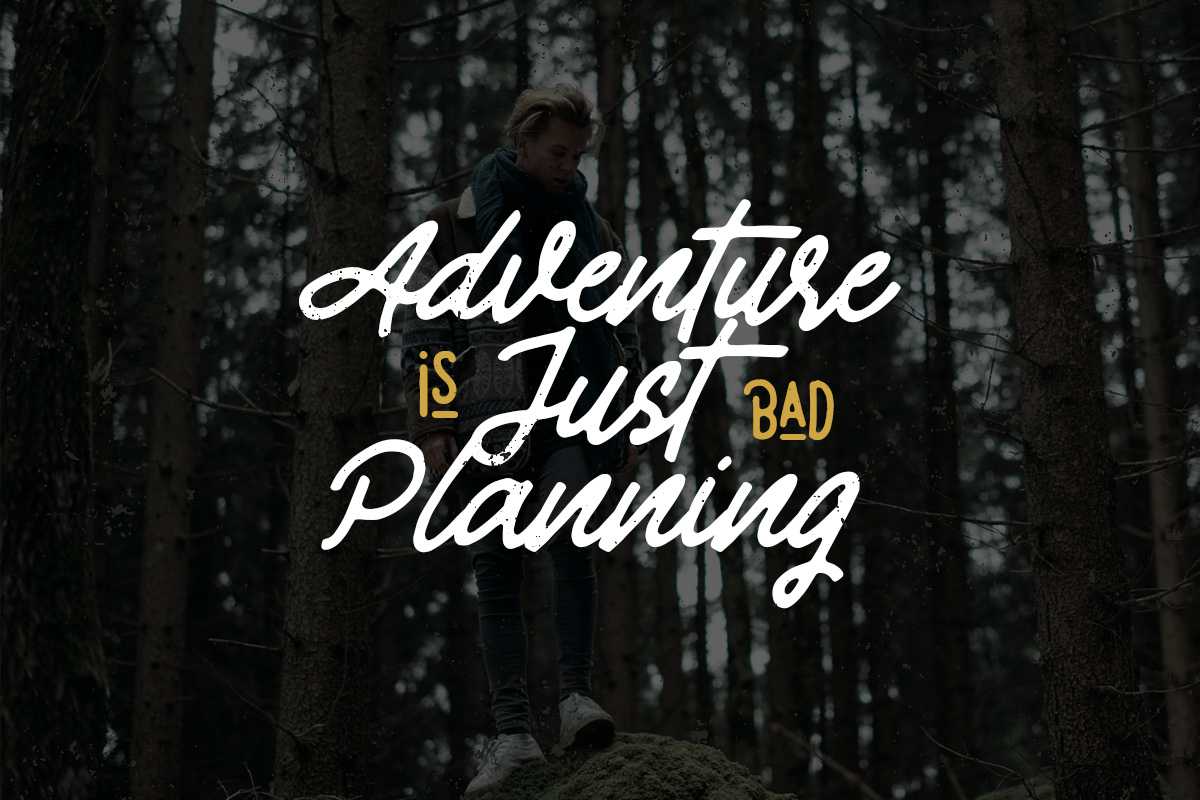
强制性的阿文塔格方多!此字体具有独特的字体和手感。可完美地使用非彩色字体/文字标记、徽章、招牌、海报、头条文字、服装、婚礼宣传等。此字体具有多种五种字体功能,包括广告、文体替代、上下文替代、swash等,支持多种语言。必填!阿文塔格方多!此字体具有独特的字体和手感。可完美地使用非彩色字体/文字标记、徽章、招牌、海报、头条文字、服装、婚礼宣传等。此字体具有多种五种字体功能,包括模仿、风格替换、上下文替换、swash等,并支持多种语言。